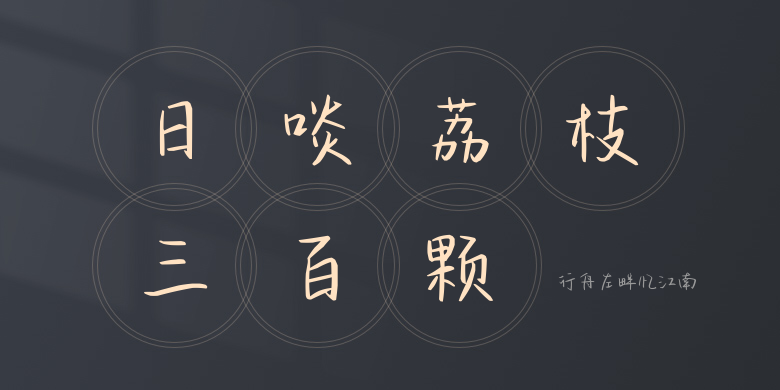
行舟左畔忆江南
行舟左畔忆江南,这款字体结构工整、笔画清晰,兼顾美观与易读性,适用于标题、正文、海报、包装、LOGO 等多种场景。字形优雅稳定,风格百搭耐看,适配日常排版与创意设计,让文字呈现更舒适、更具质感。行舟左畔忆江南一笔一画,皆是细节,以均衡的比例、流畅的线条打造舒适视觉体验,字形端正大气,风格简约现代。无论是商业设计、品牌宣传还是日常排版,都能轻松驾驭,让文字更有格调与力量。行舟左畔忆江南字体下载。